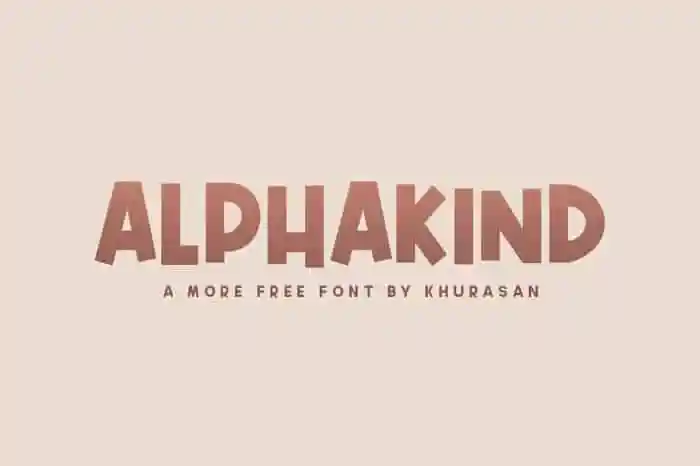
Alphakind Display Font – Download Grátis
A Alphakind Display Font é uma tipografia moderna e limpa projetada por Khurasan. Esse tipo de letra está ideal para aplicação nos títulos, logomarcas e materiais publicitários, proporcionando um design atraente e sofisticado. Seus recursos OpenType permitem ligaturas encantadoras e alternativas estilizadas que dão uma aparência única às suas criações tipográficas. Ideal para aplicação em capas de livros, banners e propaganda, Alphakind Display Font é uma ótima opção para designers buscando um tipo com atitude contemporânea.